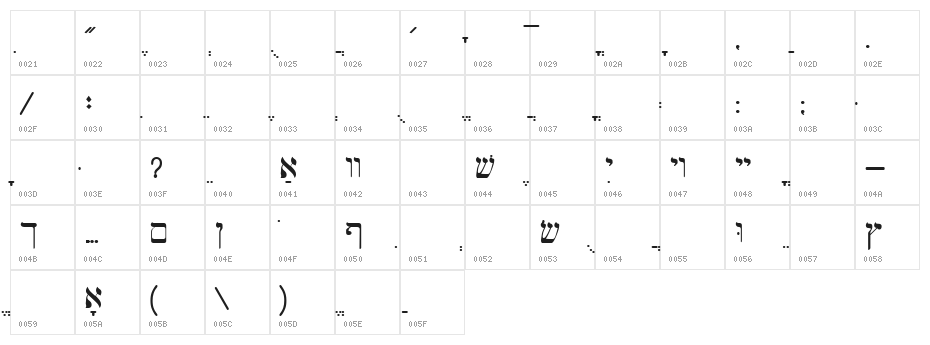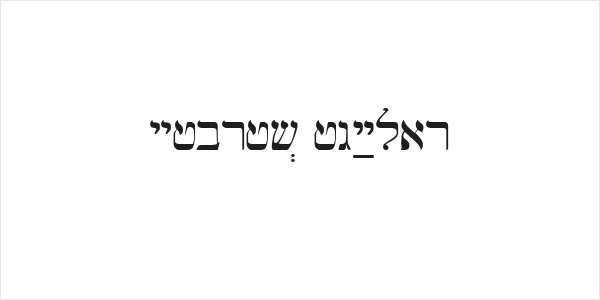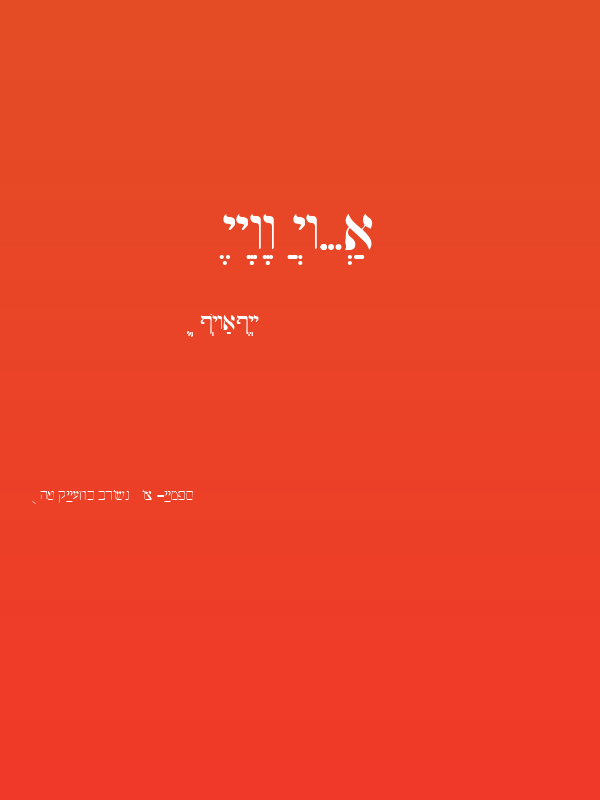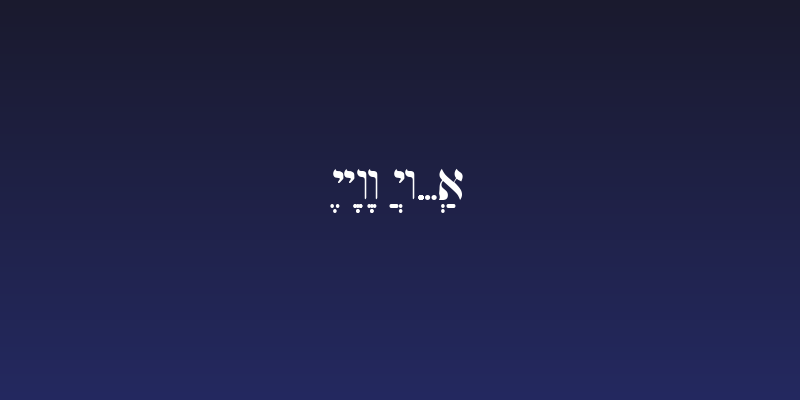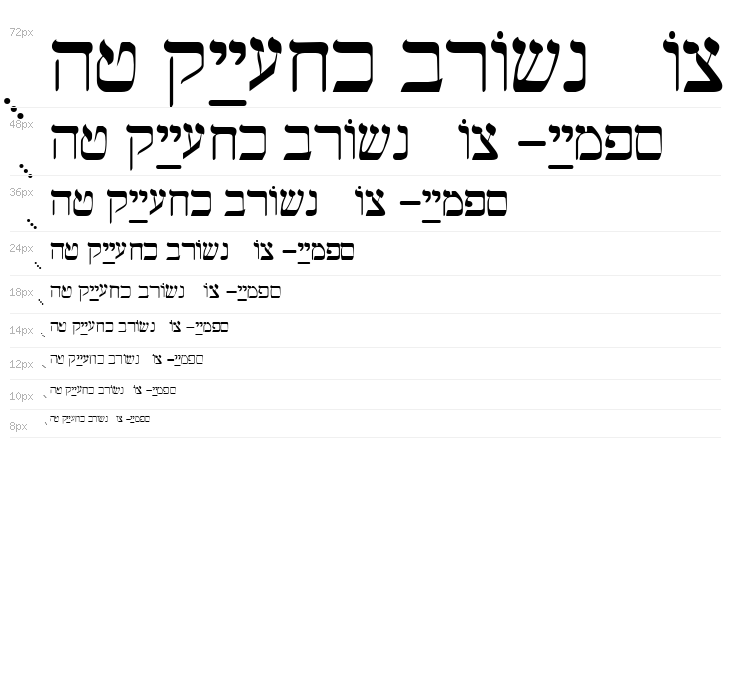
Hebrew Regular Font
| Anwendungsfall | Headlines, Logos, Cultural publications |
| Vorgeschlagene Projekte | Ideal for religious texts, cultural publications, branding for Jewish events, and educational materials. |